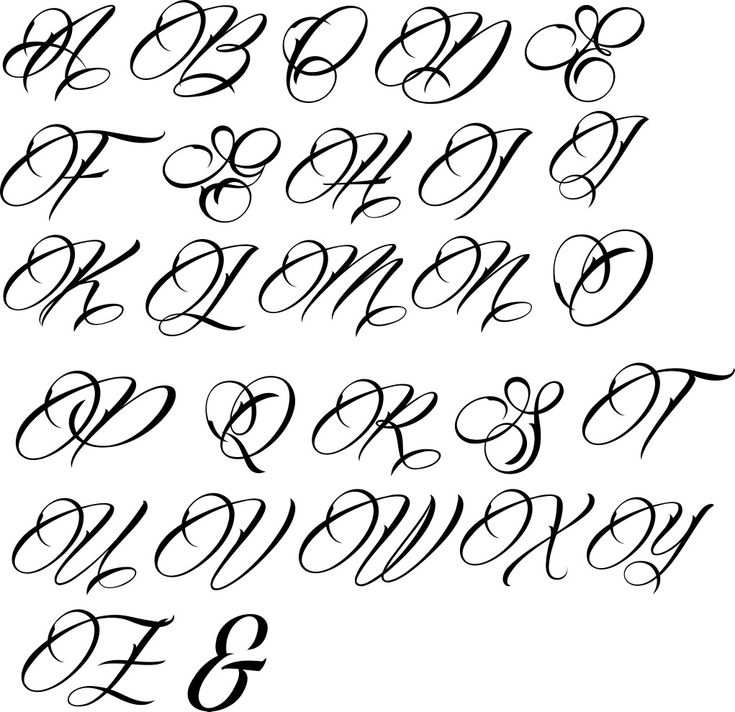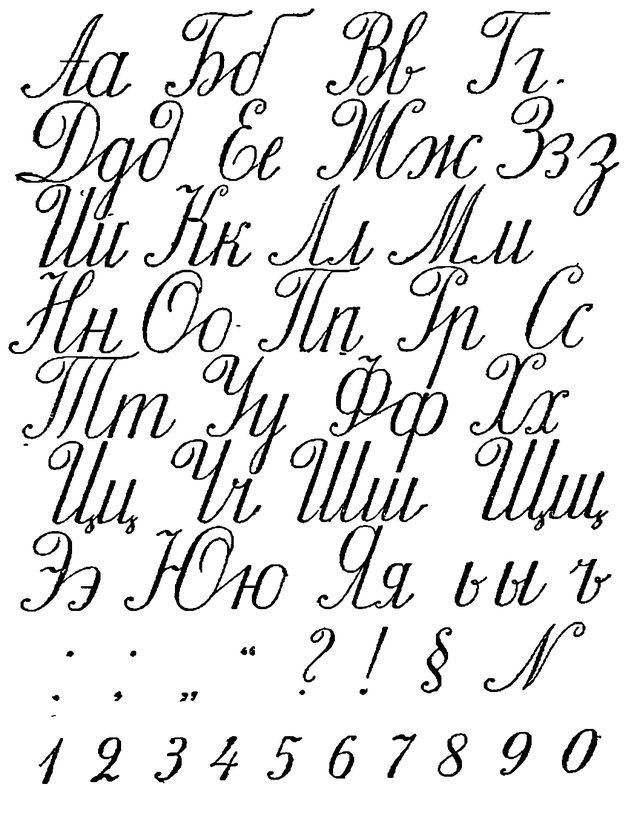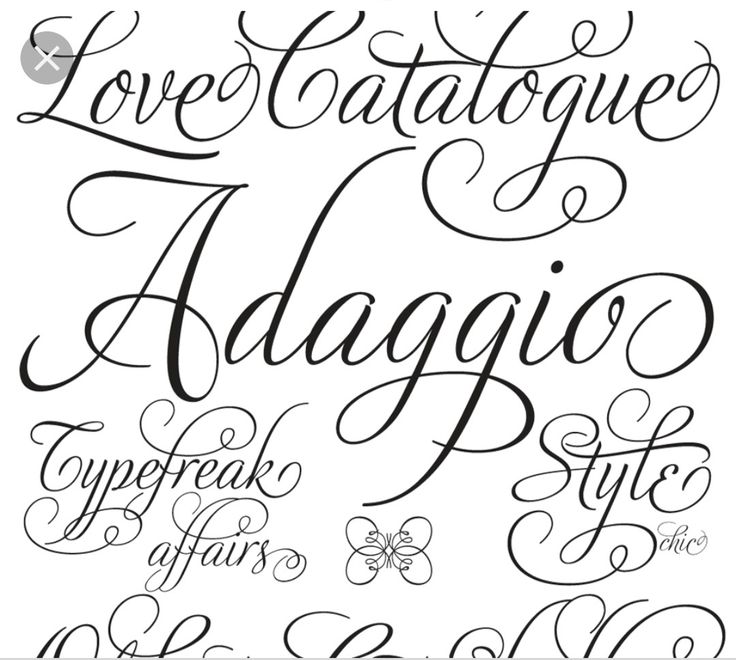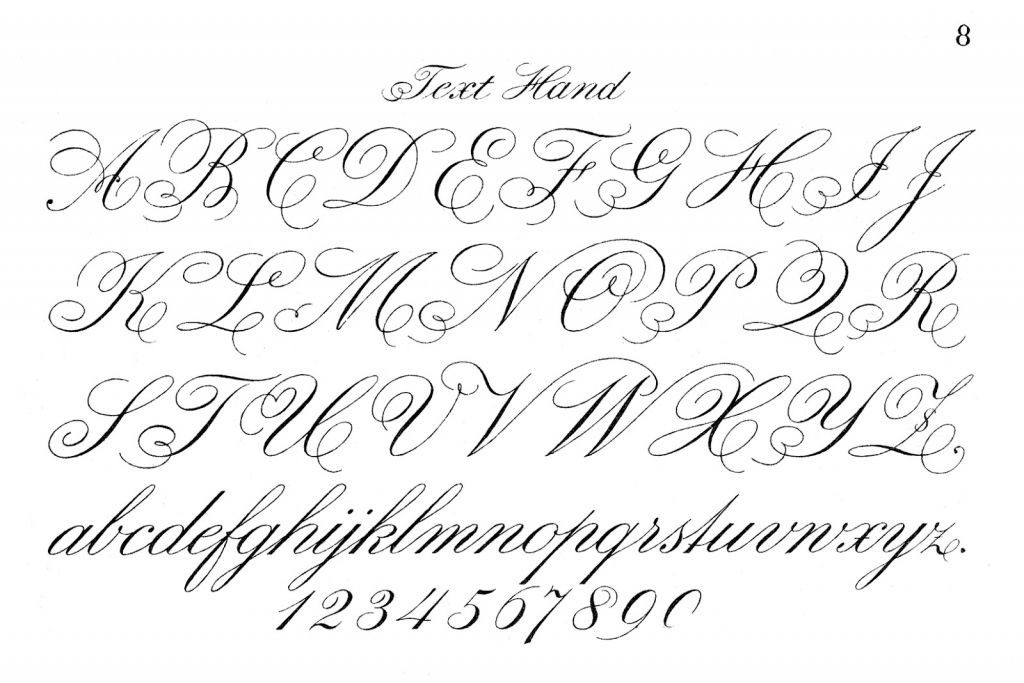
𝒮𝒸𝓇𝒾𝓅𝓉
рукописный / скорописный / почерк
Script — это попытка воссоздать рукописный почерк.
Воссоздавать курсив на экранах компьютеров смешно. Особенно когда буквы не совпадают. Использовать только в грустных ироничных целях.